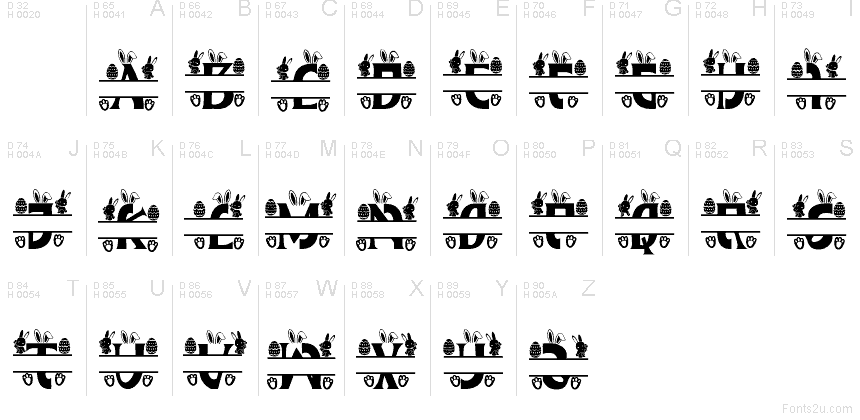
Perfect Easter Monogram
Perfect Easter Monogram da Yoga Letter é uma fonte de Páscoa gratuita com um estilo de monograma construído em torno de um painel central robusto e motivos festivos simples. O design combina coelhos, ovos e detalhes de pegadas com um tratamento de letras em negrito e estilo recortado, conferindo um visual sazonal organizado que funciona muito melhor como elemento decorativo do que como texto principal.
Perfect Easter Monogram é uma fonte gratuita para cartões de Páscoa, layouts de convites, etiquetas de presente, projetos escolares e gráficos de promoções de primavera. A sua mistura de molduras de monograma e pequenos ícones temáticos também funciona bem para logótipos, detalhes em banners, etiquetas e designs artesanais que necessitam de uma identidade festiva clara, sem ornamentos excessivos.